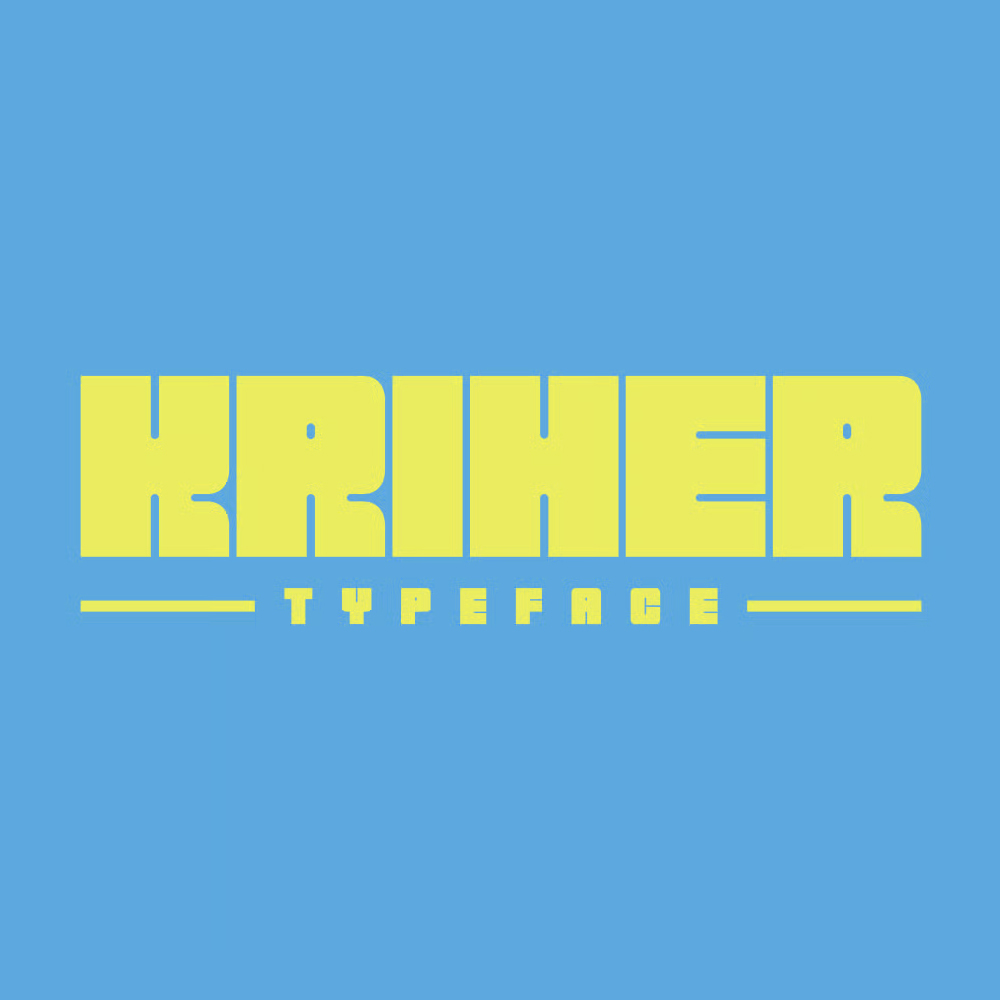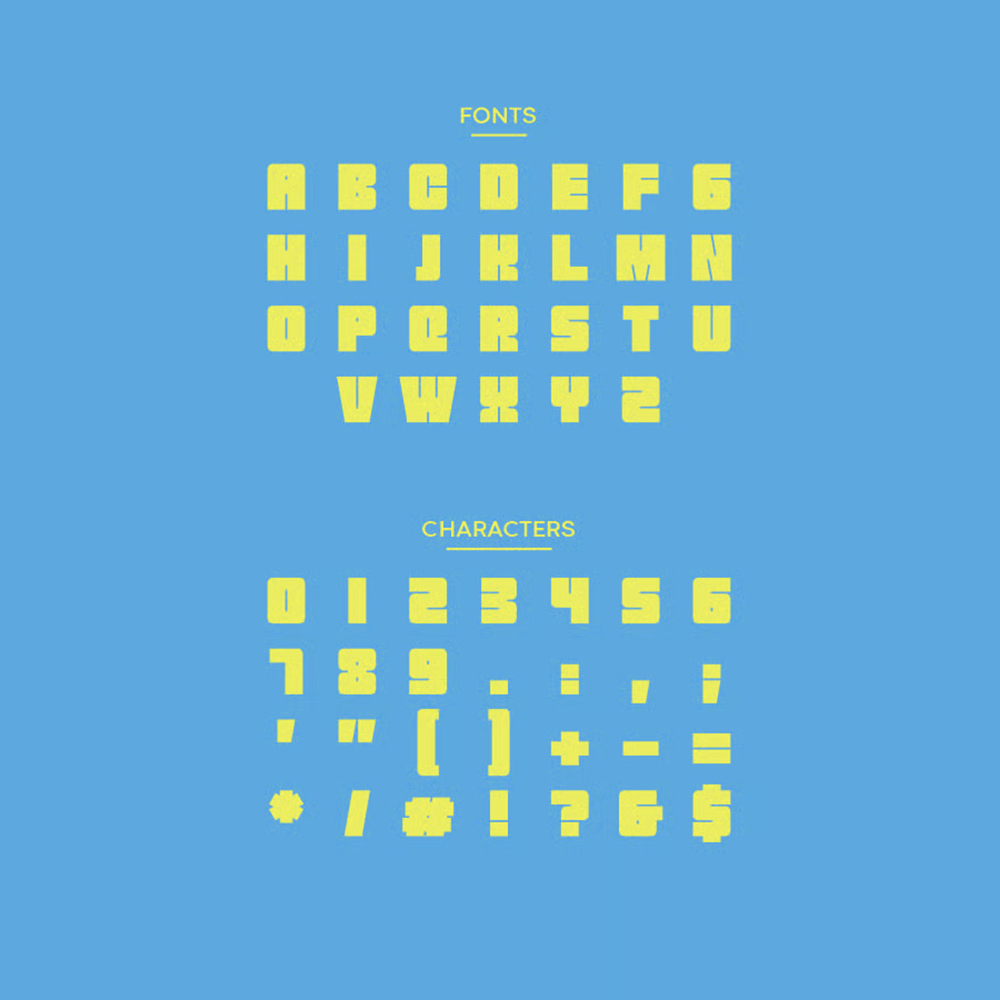
فونت پرمیوم و انگلیسی Krohur Font یک فونت جسورانه و قدرتمند با حروف بزرگ است که پیام شما را برجسته میکند. این فونت میتواند انتخاب مناسبی برای به حداکثر رساندن اهداف شما باشد. این فونت برای عناوین پوستر، طراحی بستهبندی، تیترها، لوگوها، موشن گرافیک، عناوین فیلم، تبلیغات ورزشی و فناوریهای آینده مناسب است.
مزایای استفاده از فونت لاتین Krohur چیست؟